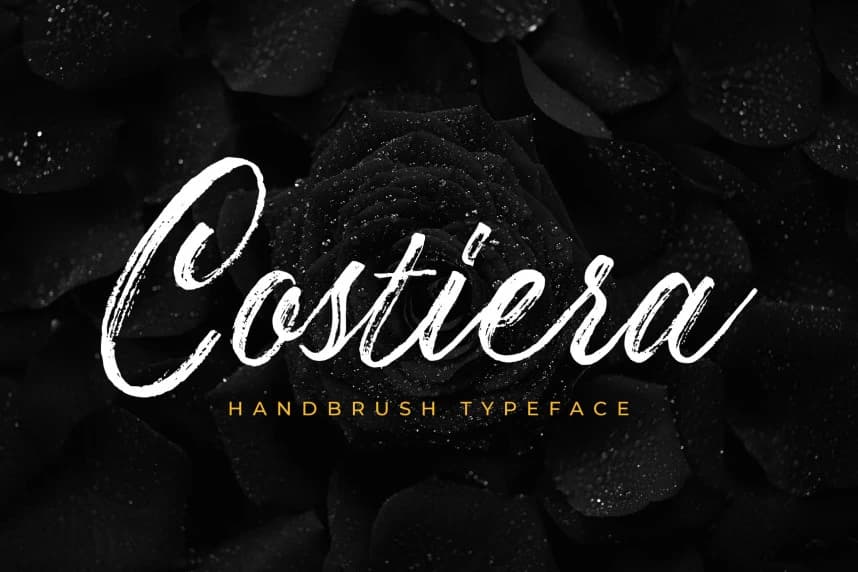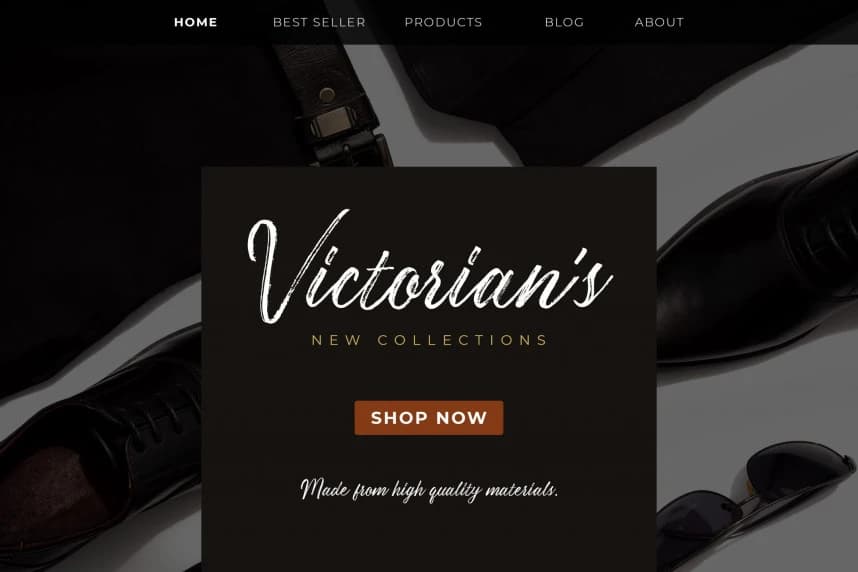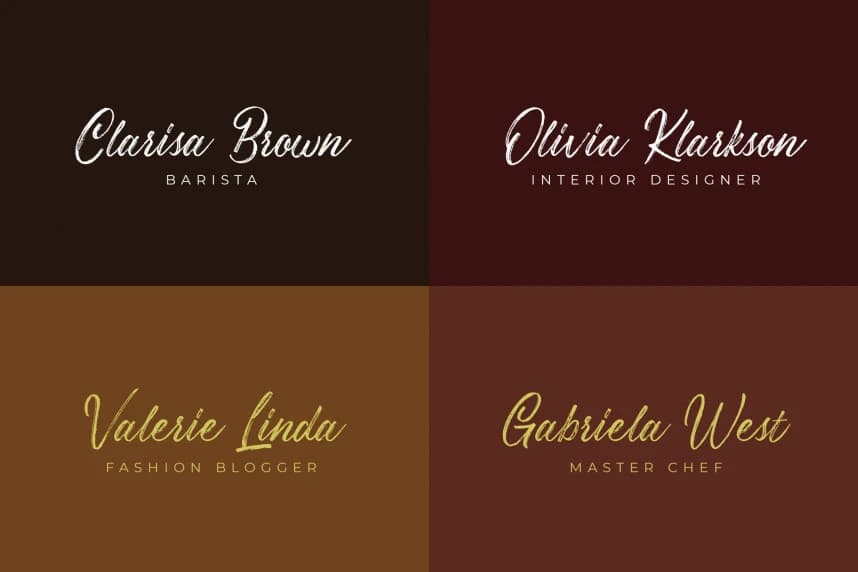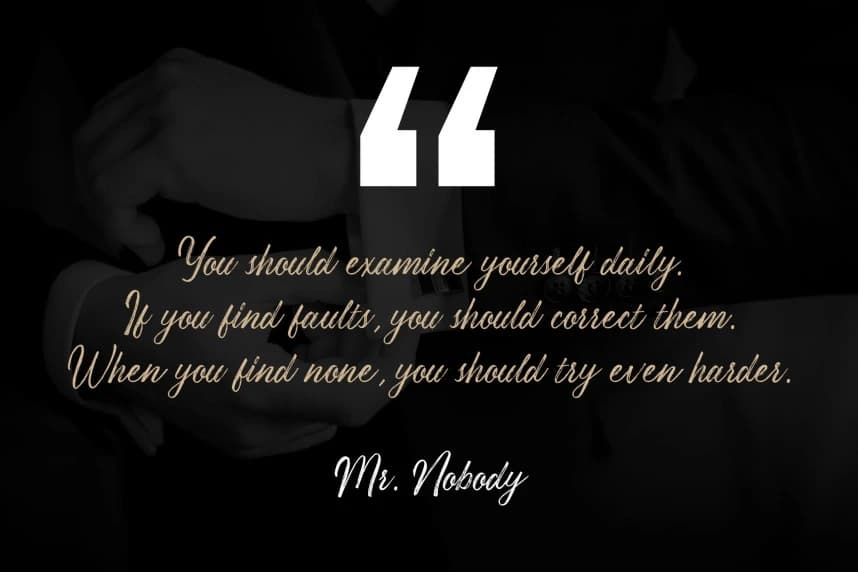
Costiera Brush Font
Costiera Brush Font – Elegant Handbrush, rahat ve hızlı yazılan bir fırça yazısıdır. Harfler kağıda fırçalarla yapılır. Sonra taranır ve dikkatlice vektör formatına dönüştürülür. Bu nedenle Costeria çekici, otantik ve rahat bir özelliğe sahiptir.
Costiera Brush Font – Elegant Handbrush gündelik ve hızlı yazılan bir fırça yazı tipidir. Harfler kağıt üzerinde fırçalarla oluşturulur. Sonra taranır ve dikkatlice vektör formatına dönüştürülür. Bu nedenle Costeria büyüleyici, otantik ve rahat bir karaktere sahiptir